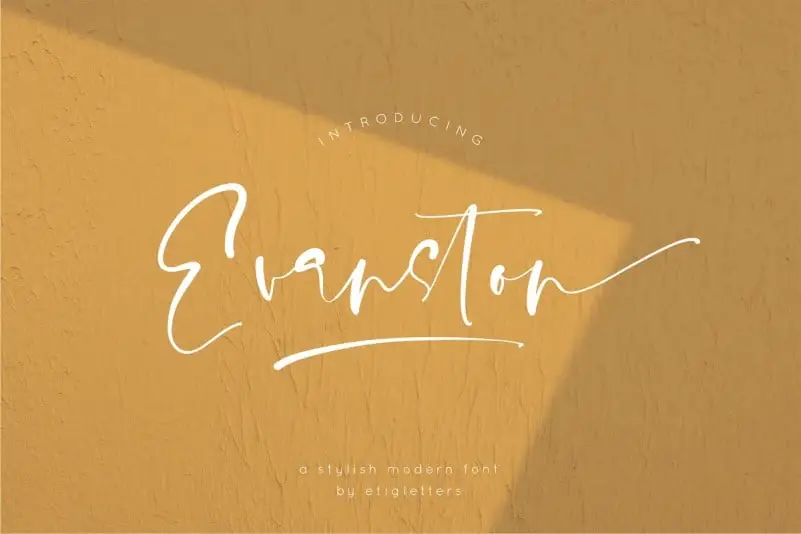
Evanston Script Font – Download Grátis
A Evanston Script Font é uma opção perfeita para quem busca uma tipografia elegante e delicada. Esta fonte foi criada por etigletters, designer do 99designs, com um estilo moderno, fluido e cuidadosamente desenhado à mão. Suas letras são arquitetadas de forma equilibrada, proporcionando uma composição harmônica que se adapta perfeitamente a vários projetos. Com sua elegância e simetria perfeita, Evanston é ideal para aplicar em sites, identidade visual, materiais de casamento e muito mais. Seu formato moderno e refinado, criado por etigletters, destaca-se como uma ótima escolha para estilos artísticos e contemporâneos.